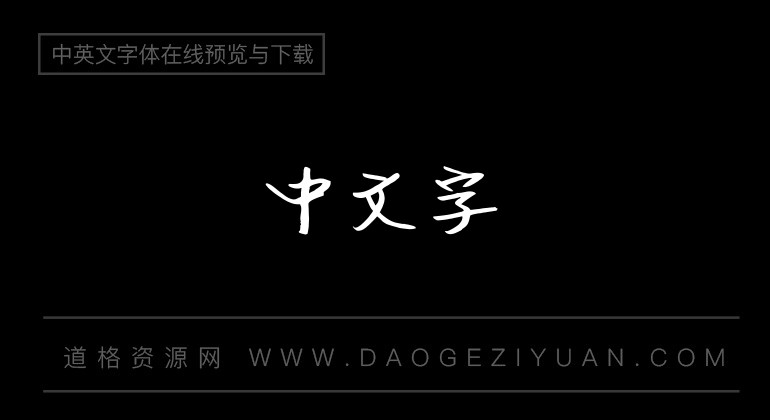
金梅宽钢笔字国际码
金梅宽钢笔字国际码是一款中国传统文化的精美字体,它源自中国古代的书法文化,具有古典的美感,流畅的笔画,坚实的结构,极具立体感,在网络中展现出清新的视觉效果,受到众多设计师的追捧。它以简洁大气的字体形式,把中国传统文化的精髓表现得淋漓尽致,为设计师提供了丰富多彩的选择,可以满足不同的设计需求。
金梅宽钢笔字国际码是一款非常不错的手写艺术字体,具有很好的视觉感,适合于文化类的宣传设计、商业类品牌的广告和产品包装设计以及个性化文字排版等较多场景。